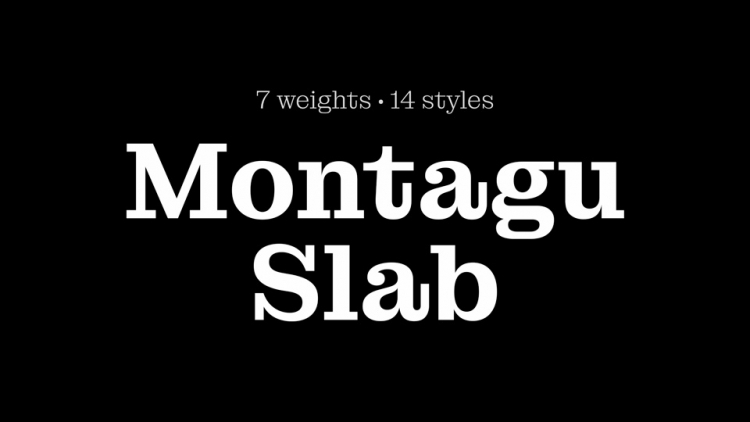
A fonte “Montagu Font Family” é uma slab serif robusta que carrega um toque delicado e humano. Inspirada no design industrial, ela combina força e estabilidade com um ar aconchegante, como se cada letra fosse moldada pelo próprio artesão. Este conjunto de fontes apresenta linhas solidas e curvas suaves em perfeita harmonia, criando um equilíbrio entre modernidade e tradicional elegância. Seja para headlines ou textos mais detalhados, “Montagu Font Family” oferece uma opção única que transmite força e simpatia ao mesmo tempo, tornando-se a escolha perfeita para qualquer projeto gráfico.